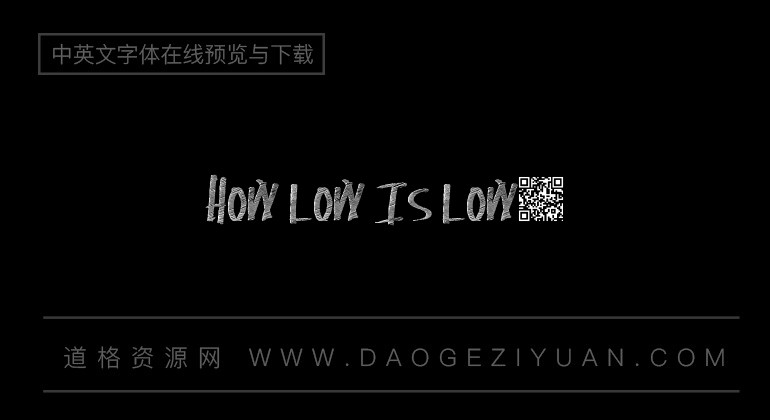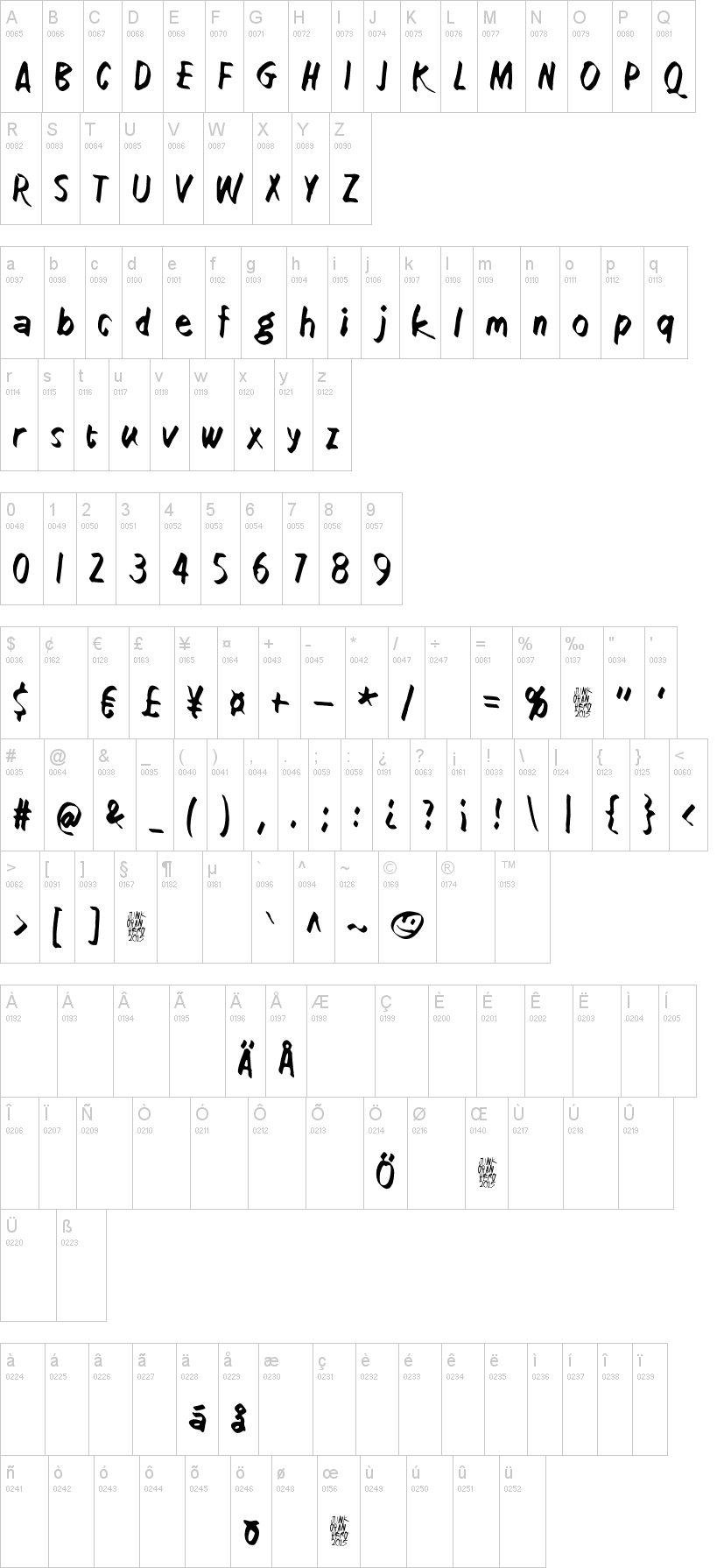
How low is low? 是一款由美国设计师Tory Novikova设计的手写字体。它是一种清新、轻松的字体,既可以用于标题,也可以用于正文。它的字母形状设计简单,但具有足够的可读性,能够让文字看起来更有趣、更有活力。它有着温暖、柔和的调调,可以为你的文字增添活力和温暖的气息。内容介绍
How low is low?是一款非常不错的手写艺术字体,具有很好的视觉感,适合于文化类的宣传设计、商业类品牌的广告和产品包装设计以及个性化文字排版等较多场景。